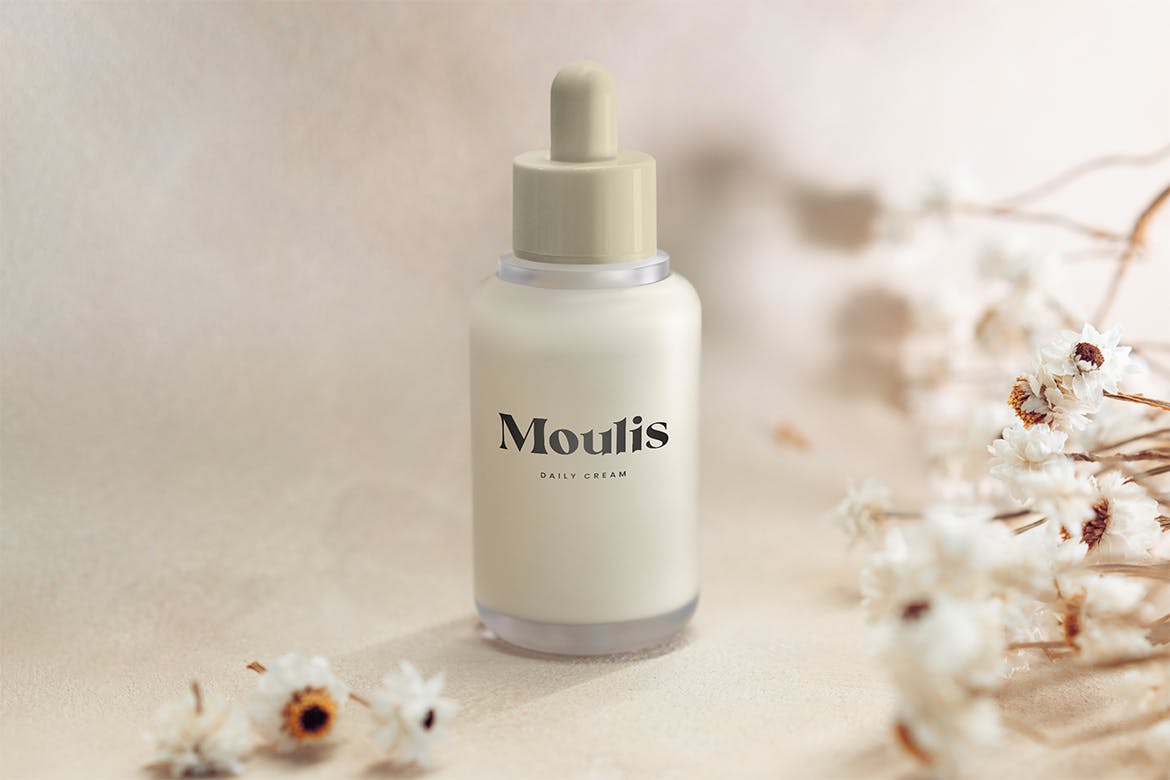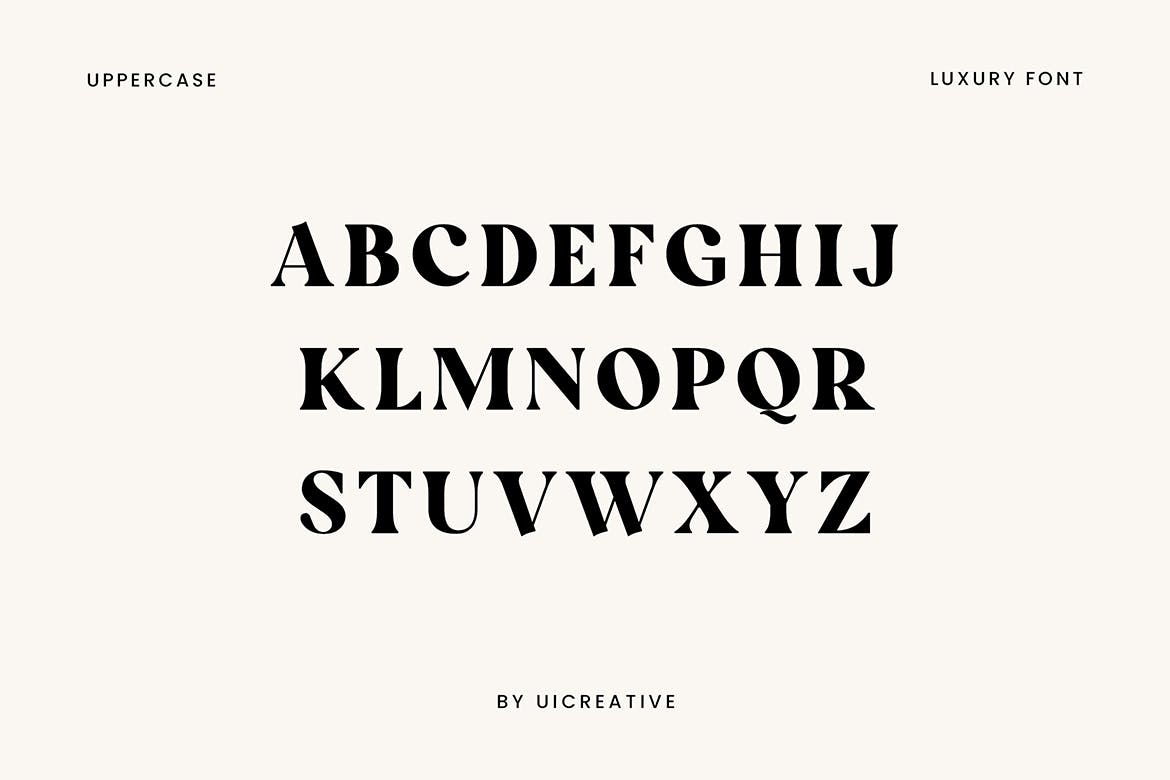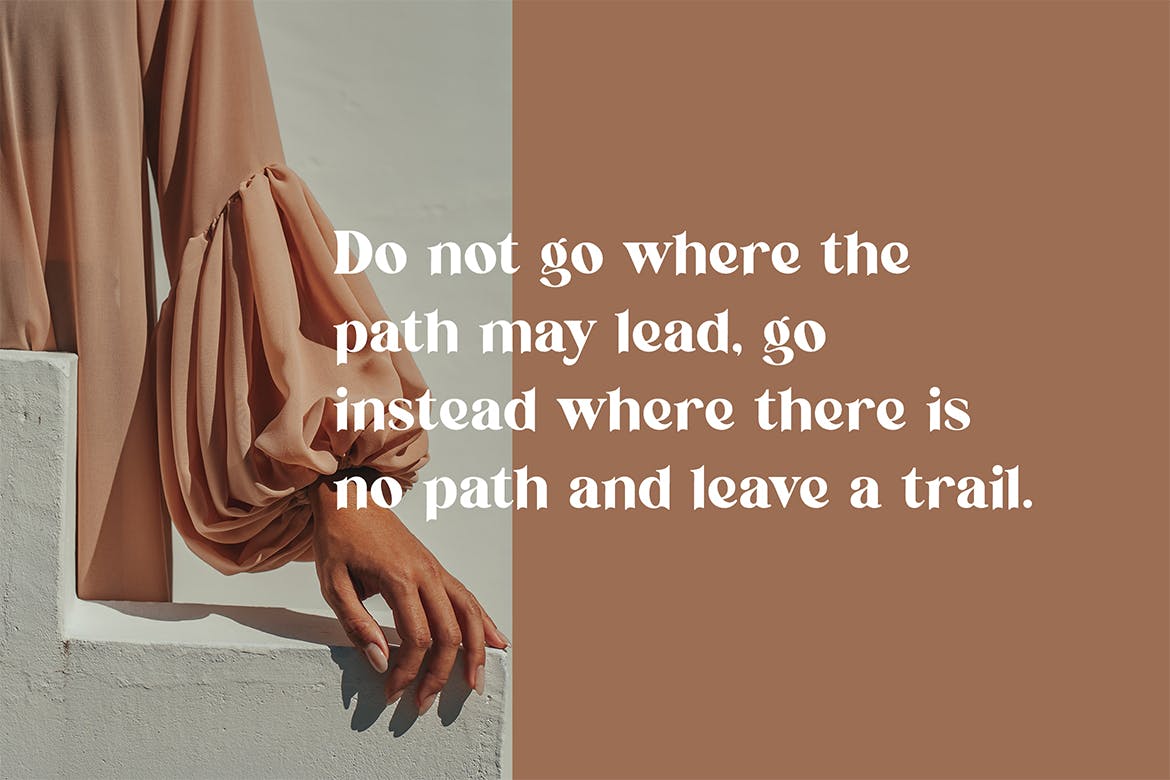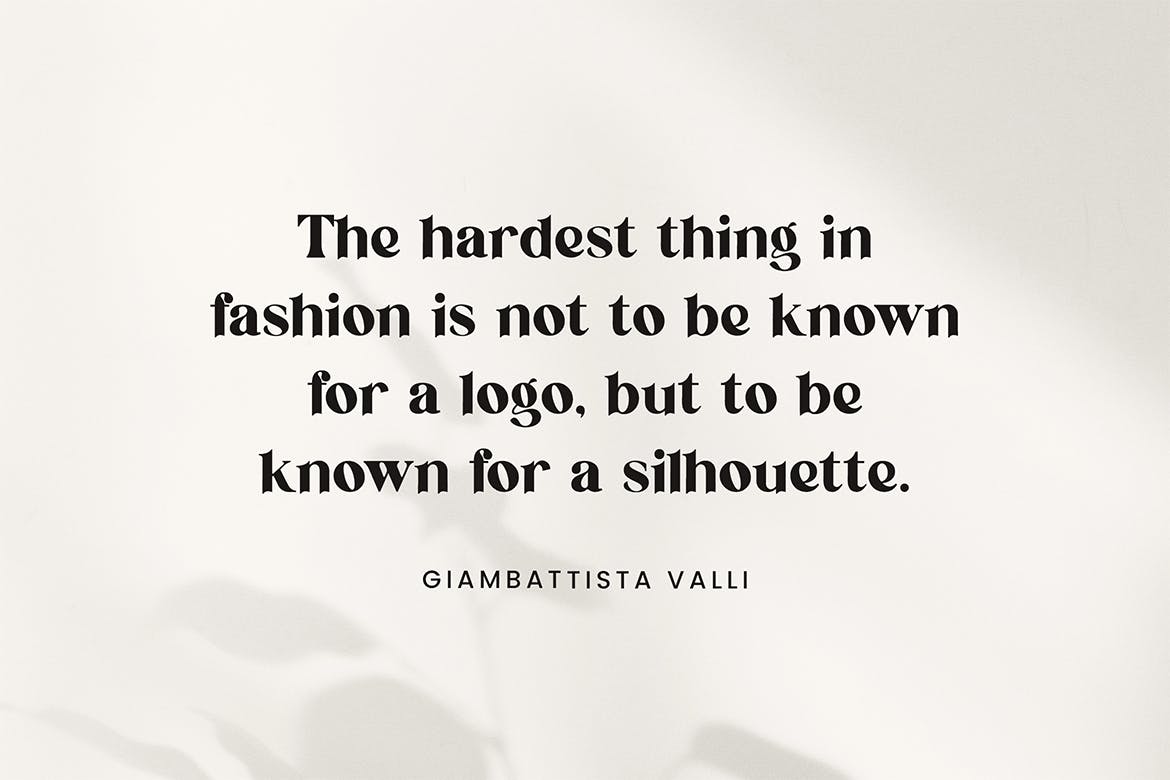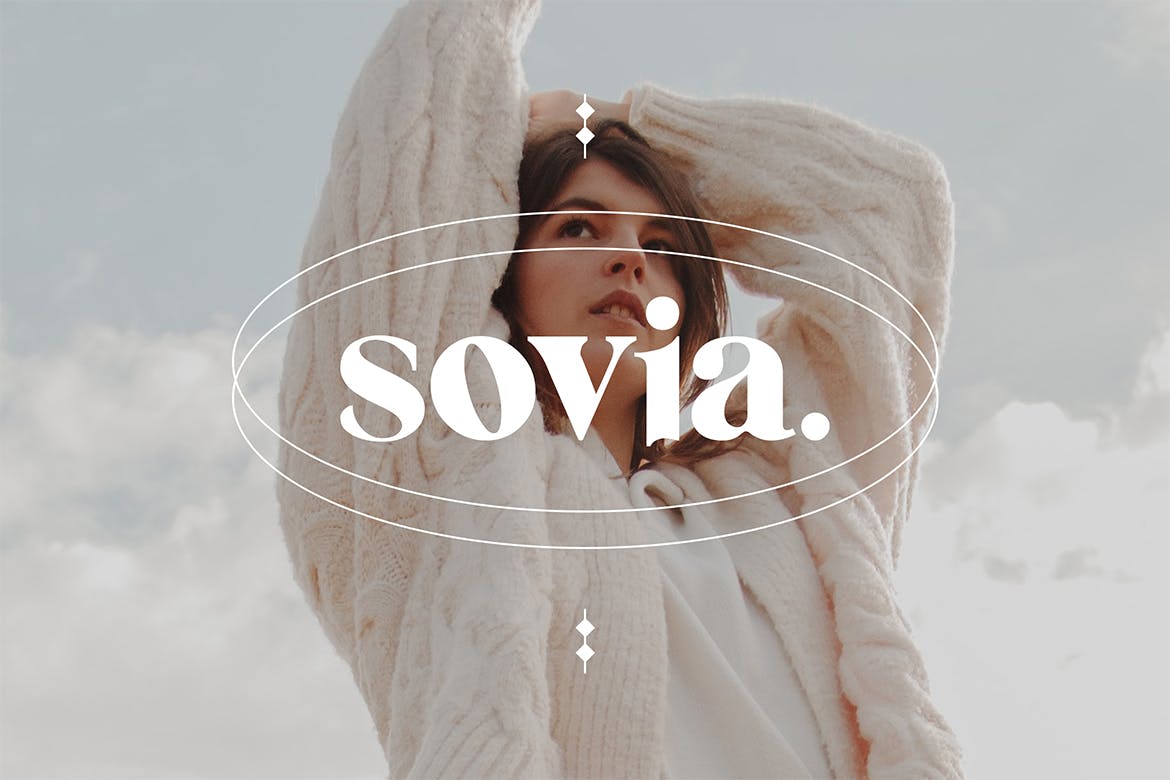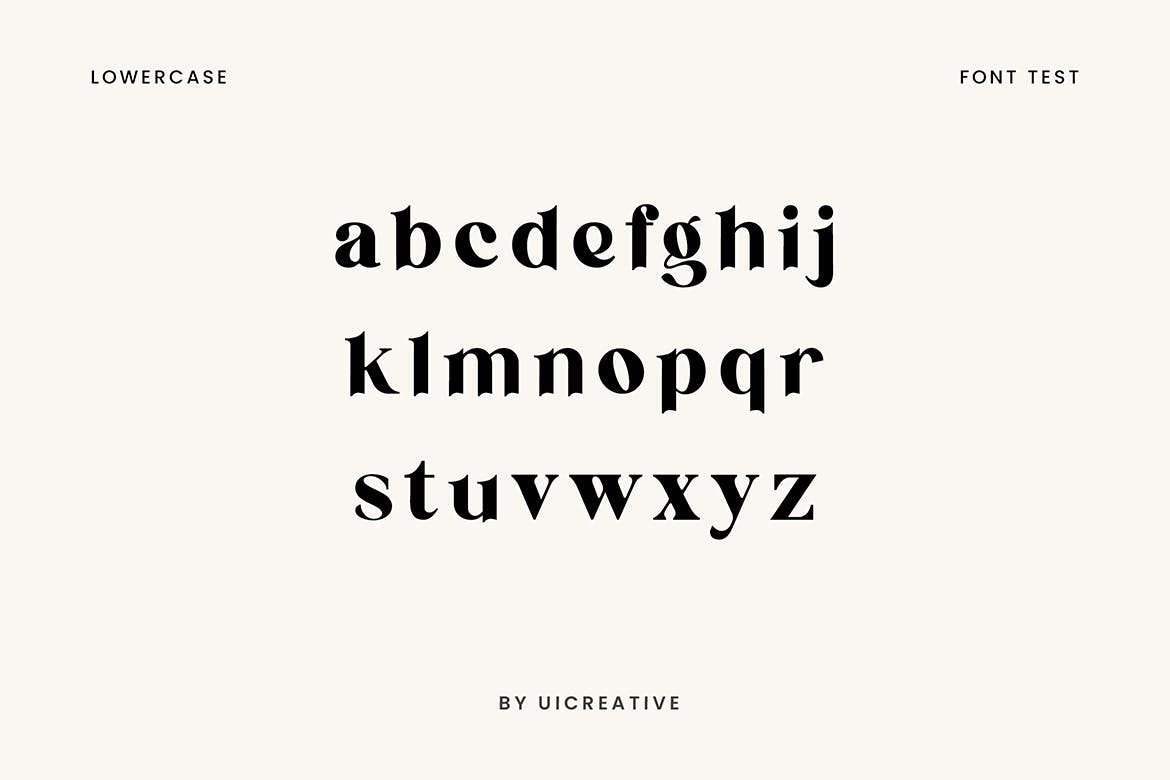
دانلود فونت میکلست لاکچری سریف با طراحی مدرن
Micklest Luxury Serif Font
فونت میکلست لاکچری سریف، مناسب برای طراحی‌های شیک و مدرن.
به شما فونت جدید و زیبای Micklest Luxury Serif Font را معرفی می‌کنیم. این فونت سریف مدرن، حس زیبایی، کلاس و شیکی را به پروژه‌های شما می‌بخشد. فونت میکلست برای انواع مختلفی از پروژه‌ها همچون امضا، لوازم‌التحریر، لوگو، عروسی، نقل‌قول‌های تایپوگرافی، جلد مجلات یا کتاب‌ها، هدرهای وب‌سایت، لباس، برندینگ، طراحی بسته‌بندی و بسیاری دیگر کاملاً مناسب است. همچنین، طراحی‌های مرتبط با برندهای مد یا ویراستاری، کیفیت‌های مردانه و زنانه را به نمایش می‌گذارد.